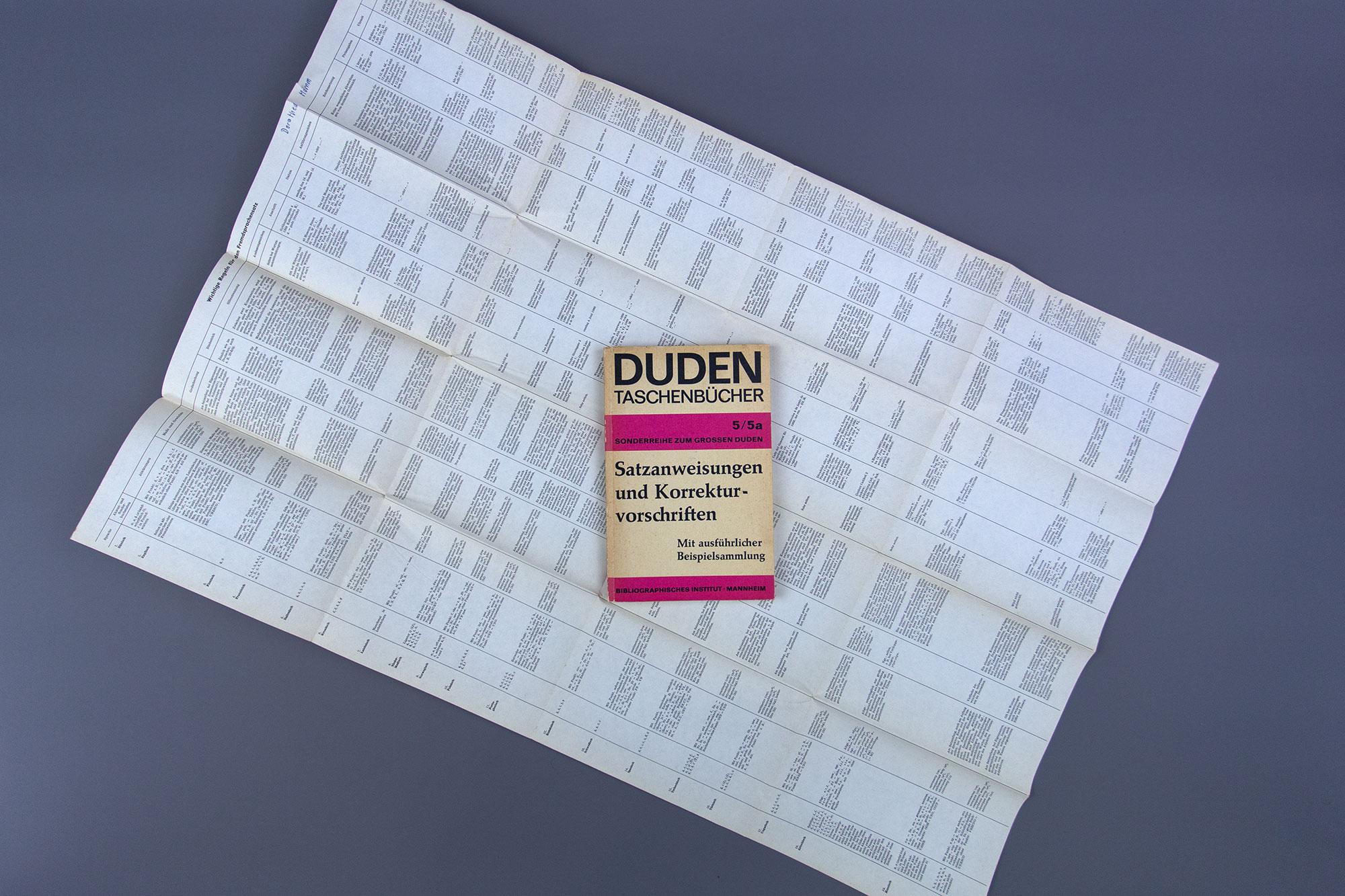
hat jemand italienische Satzvorgaben? Es geht um …
… einen per Gedankenstrich eingeschobenen Satz. Wie wird der denn richtig gesetzt?
ein Beispiel:
… connessioni wireless ,– inclusa la tecnologia UMTS/HSUPA integrata, – per restare in contatto con la propria base sempre e ovunque …
mir kommt diese Verbindung zwischen Komma und Gedankenstrich eher komisch vor... gibt es da irgendwelche Vorgben?
Brigitte Witzer (Hrsg.): Duden Satz und Korrektur. Texte bearbeiten, verarbeiten und gestalten, 2002, 440 Seiten, 24,90 Euro, Dudenverlag
8. Kapitel Richtlinien für den Fremdsprachensatz, Seite 407
Bertel,
du hast ja offenbar schon mal etwas in Italienisch gesetzt. Vielleicht weißt du ja noch die wichtigsten Regeln? Was ich jetzt so sehe, ohne mich vorher groß schlau gemacht zu haben: Gedankenstrich wie im Deutschen, Anführungszeichen und Apostroph wie im Englischen.
Sowas ist falsch: un bell´esempio, richtig: un bell’esempio
Wie war das mit dem Streckenstrich? Wird der verwendet?
Die Simoneitschen Anführungszeichen “„ für Italienisch und Ungarisch hab ich mein Lebtag noch nicht gesehen, auch nicht in türkischen Überschriften.
Ich kenn es so:
“Italienisch”
„Ungarisch”
Als Apostroph wird ein Apostroph verwendet, aber das ist keine italienische Spezialität, sondern weltweit so. Zumindest ist mir keine Ausnahme bekannt.
un bell´esempio | falsch
un bell'esempio | falsch
un bell’esempio | richtig
– Gedankenstrich wird wie im Deutschen verwendet. (Halbgeviertstrich)
– Bisstrich ist im Deutschen so lang wie der Gedankenstrich, im Italienischen wird aber der kurze Bindestrich als Bisstrich verwendet
– Streckenstrich war im Italienischen der Geviertstrich, den kenn ich heute aber auch eher als Halbgeviertstrich.
Witzer schreibt (neben Ausführungen zu Abkürzungen, Großschreibung, Anführungszeichen, Zahlen, Datum, Maße und Gewichte, Preisangaben, Anschrift, Silbentrennung) nur diesen einen Satz zur Zeichensetzung:
Sie ähnelt der deutschen, doch steht das Komma nicht vor Nebensätzen mit che (= dass) sowie se (= ob, wenn) und nicht vor Infinitivsätzen.
Ob Bertel damit geholfen ist?
Die findet man in wissenschaftlichen Texten bis etwa Anfang der Neunziger, als es in Italien üblich wurde, dass die Verlage einfach die unbearbeiteten Word-Dokumente der Verfasser druckten.
Und mein Siemoneit ist von 1989. Vielleicht sollte ich ihn mal ausrangieren.
Hellwig, Wilhelm: Der Satz und die Behandlung fremder Sprachen. Frankfurt a. M.: Klimsch, 1930:
Der Gedankenstrich steht weniger bei unvollendeten Gedanken, als vielmehr im Gesprächsatz bei jedem Wechsel der Sprechenden, oder auch als verstärkende Interpunktion beim Punkte usw. Unausgeführte Gedanken zeigt der Italiener durch unmittelbar aneinandergereihte Punkte an, welche am vorhergehenden Worte ohne Zwischenraum anstehen […]
Tja, Bertel, das hilft dir wahrscheinlich ebenso wenig weiter. Zum Zusammentreffen von Komma und Gedankenstrich habe ich nichts finden können.:-(
Was die Zeichensetzung in Fremdsprachen anbelangt, überlasse ich das mittlerweile komplett dem Autor und – falls beauftragt – dem Korrektor oder Lektor . Die Diskussionen mit Kunden über korrekten Satz wurden mir irgendwann zu blöd.
Dann steht meinem ersten italienischen Text nichts mehr im Wege.
(Man layoutet sich sprachlich so langsam durch die Weltgeschichte.)
Ich habe gar nicht auf das Datum geachtet. :aschehaupt:  Beim Lesen habe ich mich noch gewundert, dass keine auf das Komma-Gedankenstrich-Problem eingegangen ist.
Hallo zusammen!
Ich habe ein ähnliches Thema und dachte, dass ich es einmal mit meiner Frage probiere. Ich bin Gestalterin und setze häufiger die gleichen Layouts mit deutschen, englischen, polnischen, französischen, niederländischen sowie schwedischen Inhalten. Bei dem Satz im Deutschen kenne ich mich aus, bei den anderen Sprachen nur wenig bis gar nicht.
Wirklich schade, da wäre ich mal bereit Geld für ein passendes Buch auszugeben und es gibt keins auf dem Markt... Falls ihr doch noch Ideen habt, würde ich mich freuen!